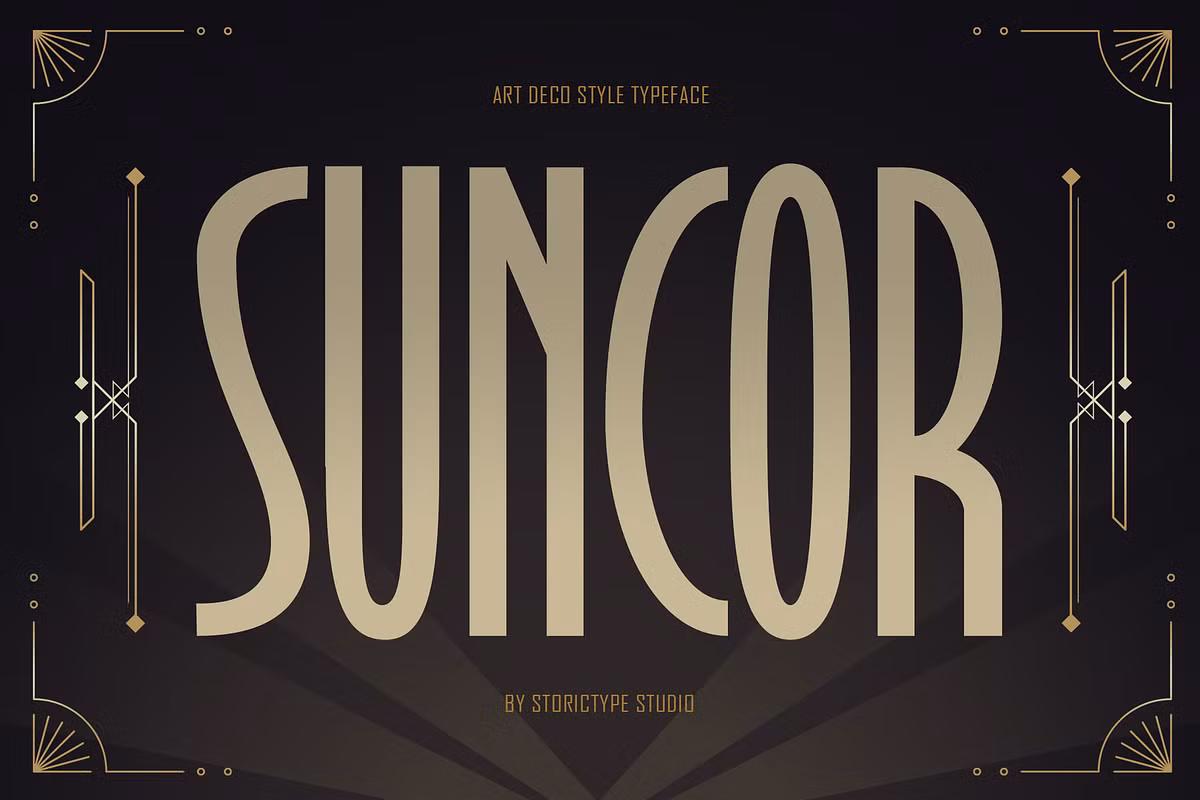
دانلود فونت Suncor – Art Deco Style Font
معرفی Suncor یک فونت جدید با سبک آرت دکو. با یک سبک کلاسیک و ظریف، به طراحی محصول شما حسی کلاسیک، مدرن و ظریف می بخشد، که برای افزودن یک لمس منحصر به فرد به لوگوها، هویت برند یا طرح های تایپوگرافی مدرن عالی است.
از این فونت می توان در طرح های مختلفی برای محصولات شما مانند بنر، لوگو، بسته بندی محصولات، لباس، مد، غذا، لوازم التحریر، تم عروسی و … استفاده کرد.